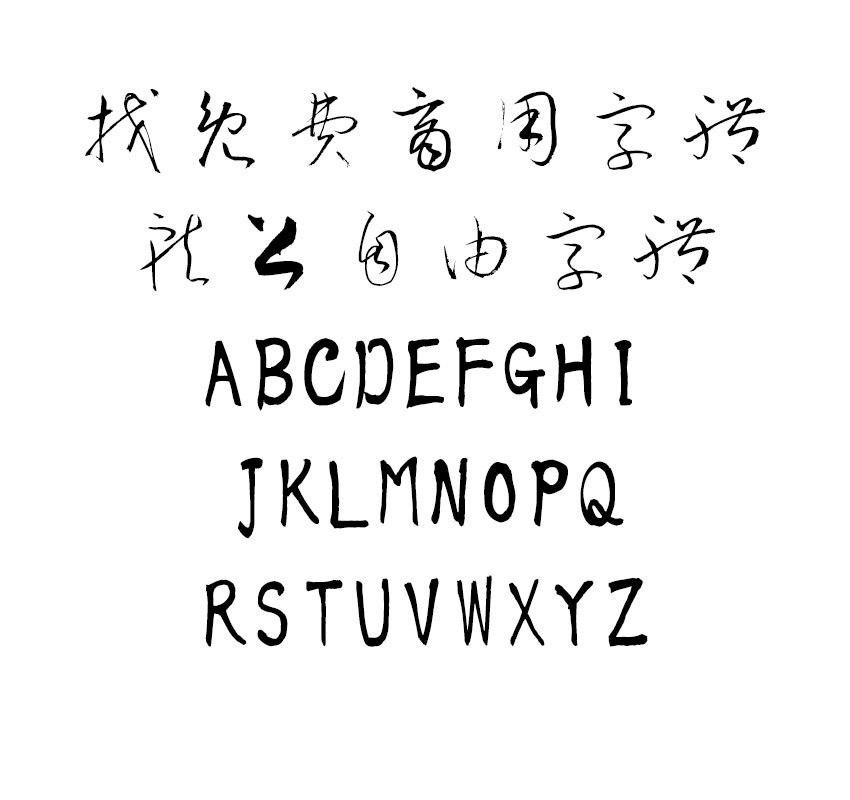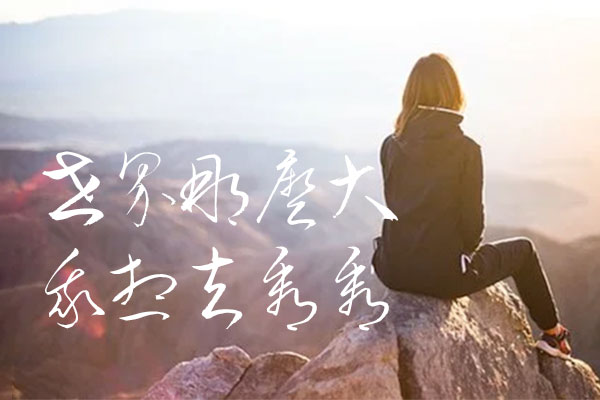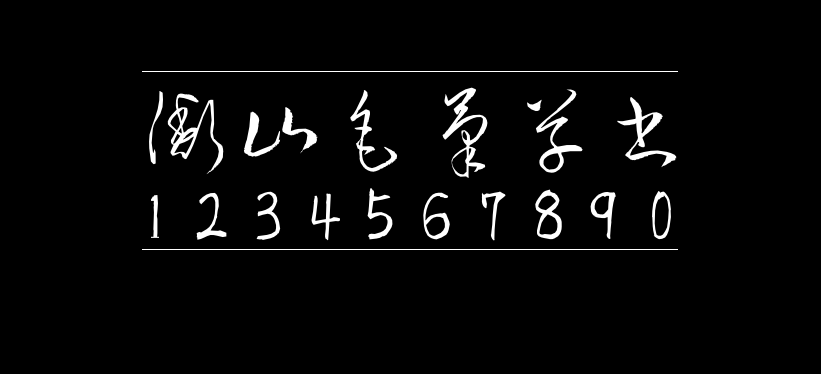
字体下载 衡山毛笔草书
衡山毛笔草书
衡山毛笔草书( 衡山毛筆フォント草書 / KouzanBrushFontSousyo)是日本书法家青柳衡山先生挥毫写成的毛笔字体,这款字体行笔潇洒飘逸, 对历史相关的漫画和设计等非常有用,是非常帅气的字体。 这款字体包含JIS第1水准2965字,第2水准3390字。
由于字体采用的日本的JIS标准,所以支持的简体字数不算多,但是繁体却是比较齐全的。